17 种最佳云字体 ️ 2023(免费和付费)
已发表: 2023-09-09您是一名平面设计师,正在寻找完美的字体来使您的项目栩栩如生吗? 别再犹豫了! 在这篇博文中,我们将深入探讨云字体的世界,并探索 2023 年可用的最佳选择。
无论您是经验丰富的专业人士还是刚刚起步,这些字体都一定会增强您设计的视觉吸引力。
现在,您可能会想,“云字体到底是什么?” 好吧,让我来告诉你。云字体是一种存储在云端而不是安装在您的计算机上的字体。
这意味着您可以从任何地方、在任何设备上访问它们,而无需手动安装。 很酷,对吧?
在本文中,我们将展示 2023 年排名前 17 的云字体,包括免费和高级选项。 我们将重点介绍它们的独特功能、多功能性以及它们如何提升您的设计项目。
无论您是为网站寻找干净、现代的字体,还是为儿童读物寻找俏皮、异想天开的字体,我们都能满足您的需求。 因此,让我们立即开始探索这些令人难以置信的云字体,它们一定会将您的设计提升到一个新的水平。
最佳高级云字体
希望通过一些一流的排版来提升您的设计项目? 我们精心挑选的最佳优质云字体就是您的最佳选择。 相信我,你不会想错过这些美景的。 看看吧,让你的创意源源不断!
云面包
Cloud Bread 是一种甜美友好的显示字体,拥有大胆可爱的形状。 其独特的风格非常适合各种设计项目。 让自己受到云面包的启发,释放您的创造力,制作出有趣且真正令人难忘的东西!
克劳德
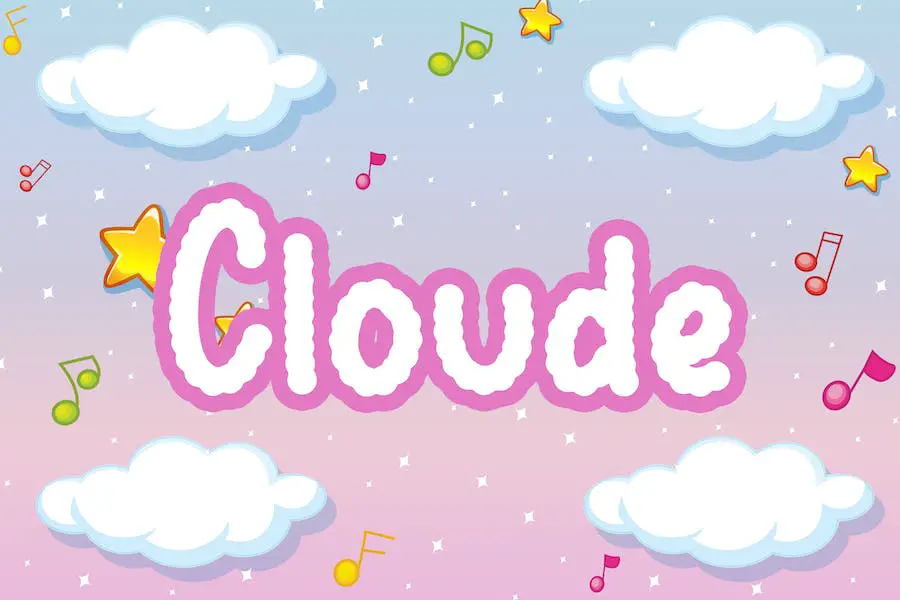
Cloude – 一种非凡的显示字体,为儿童主题设计增添兴奋感! 它非常适合品牌推广、徽标设计、T 恤、书籍封面、社交媒体帖子、广告、产品包装、标签、邀请函等。 Cloude 为任何项目带来独特的风格。
软云
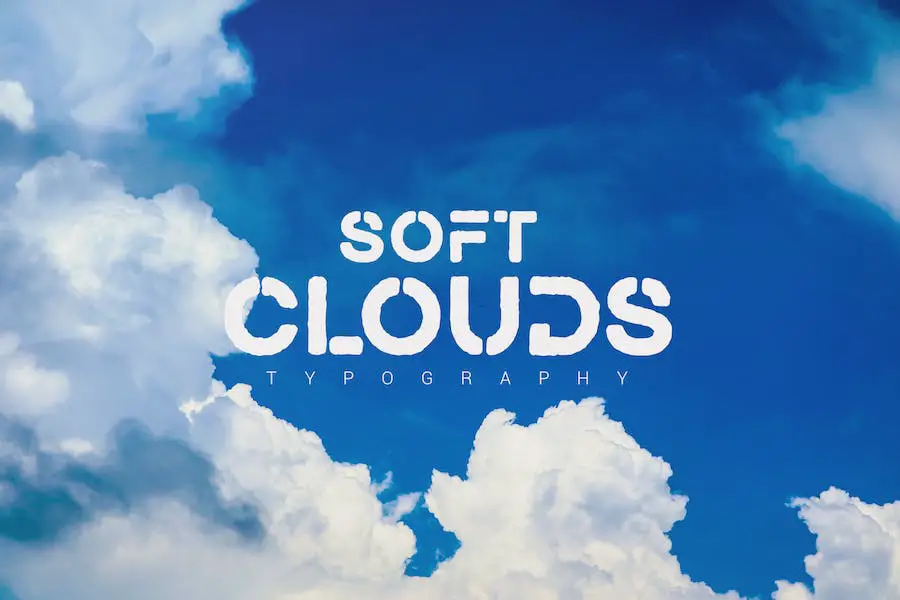
Soft Clouds 是一款出色的字体,提供三种匹配样式,为您的设计项目提供广泛的可能性。 这种字体具有易于阅读的字母,非常适合数字和印刷应用。
无论您是为网站、广告甚至纹身沙龙创建图形,Soft Clouds 都一定能为您的作品增添一丝优雅和独特。
泡沫或云
Foam 或 Clouds 是一种独特的字体,可为 SVG 字体提供逼真的笔刷效果。 它有两种样式:浅色背景上的深色字体,具有多层效果,以及深色背景上的浅色字体,具有屏幕图层效果。
云
The Clouds 是一款出色的字体包,提供 5 种匹配字体,为您的设计项目提供无尽的多功能性。 这些字体无缝地协同工作,让您可以在设计中创造出令人惊叹的变化。 无论您从事数字项目还是印刷项目,这种字体都非常易于阅读。
当谈到图形设计时,找到完美的字体可以让一切变得不同。 有了 The Clouds,您将拥有一系列字体,这些字体不仅相互补充,而且还提供广泛的创意可能性。
每种字体都有自己独特的风格,让您可以尝试并找到最适合您的项目的字体。
榛云
Hazel Clouds 是一款令人惊叹的脚本字体,提供清新和现代的外观。 无论您是从事品牌项目、创建迷人的标题、设计服装还是设计包装,这种字体都是完美的选择。
模仿小丑
Mockey Clown 是一种字体样式,可为您的设计增添动感和奇思妙想。 这种字体具有圆润的边缘、流畅的线条和稍微大胆的外观,非常适合创造时尚和现代的外观。
它提供三种不同的风格,可以混合搭配,让您的设计实现定制化和多功能性。
无论您是在从事面向青年的项目、杂志布局、海报、时尚品牌,还是只是需要为背景图像添加时尚的文字叠加层,这种字体都是时尚且可定制的选择。
扭云
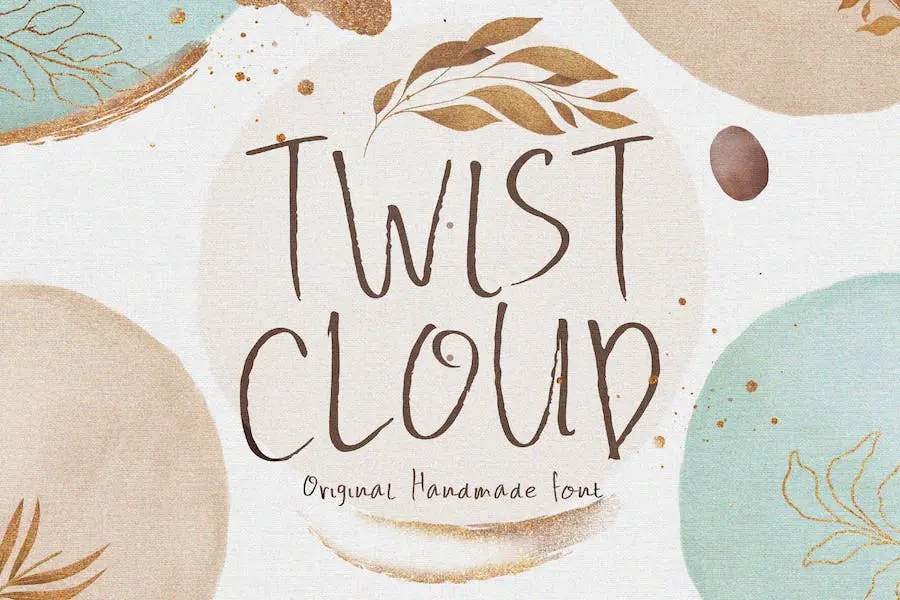
Twist Cloud 是一款将为您的企业带来独一无二的外观的字体。 凭借其独特的手写风格,这种字体可以让您以脱颖而出的方式表达您的品牌个性。
手写完全取决于个性,而这正是您通过 Twist Cloud 所获得的。 每个字母都有其独特的个性,为您的品牌增添个人风格。
无论您是要创建海报、信件、标题、网络博客、社交媒体帖子、故事、横幅、包装、T 恤设计、婚礼请柬还是徽标,这种字体的用途广泛,足以适合任何项目。
云雾缭绕
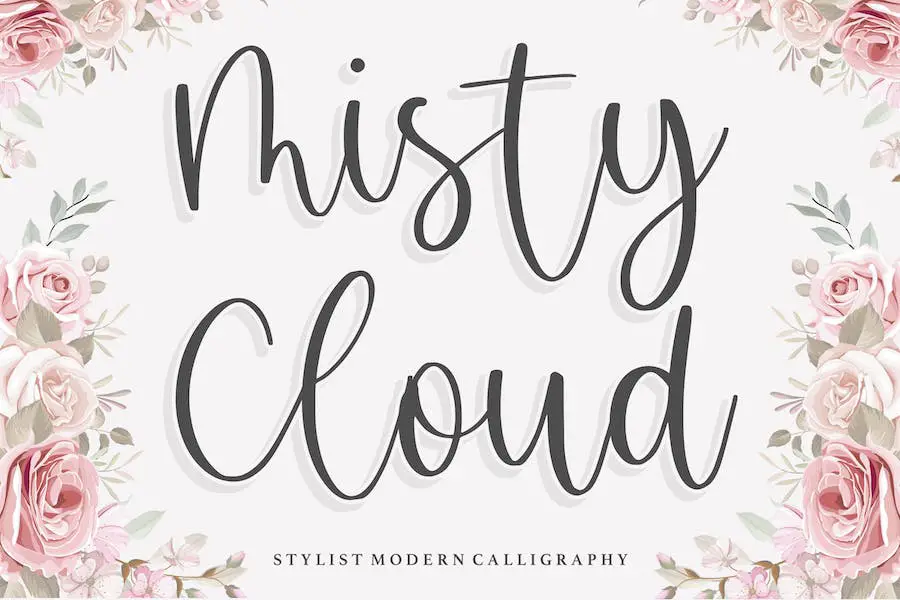
Misty Cloud 是一种时尚的现代书法字体,是任何图形设计师工具包的完美补充。
无论您是在设计产品包装、品牌项目、杂志布局、社交媒体内容、婚礼请柬,还是只是想为您的设计添加富有表现力的触感,Misty Cloud 都能满足您的需求。
蓬松的
Fluffy 是一种令人愉悦的字体,可为任何设计项目带来可爱和异想天开的感觉。 这种字体以其柔软和棉质的外观,捕捉到了空气的轻盈和手写字母的魅力。
Fluffy 的灵感源自云朵和豆子的形状,非常适合在儿童读物、卡通、动画等中营造俏皮而温柔的氛围。
这种字体的蓬松特征使其真正独一无二。 其柔和的曲线给人一种舒适和温馨的感觉,而手写字母般的形式增添了一丝真实感。
棉花云
Cotton Cloud 是一种让人联想到在天空中柔软蓬松的云中飞翔的感觉的字体。 它非常适合增强冒险在线游戏、海报、电影标题、杂志、YouTube 封面、缩略图和社交媒体页面封面的设计。
凭借其轻盈梦幻的外观,棉花云为任何项目增添了一抹奇思妙想。 该字体用途广泛,可在各种环境中使用,使其成为寻求提升设计的图形设计师的绝佳选择。
吉特哈
Jitqha 是一种可爱又有趣的字体,非常适合各种设计项目,尤其是针对儿童的设计项目。
它采用大写字母,为生日邀请函、文具、T 恤设计、标签、徽标、品牌、包装甚至日历增添了有趣和异想天开的感觉。
无论您是在从事儿童活动项目,还是只是想为您的设计带来有趣的元素,Jitqha 都是一个不错的字体选择。
最佳免费云字体
为希望增强项目设计的图形设计师推出一系列最佳免费云字体。 花点时间浏览这篇文章,找到可以提升您的创意作品并使其真正脱颖而出的完美字体。
云
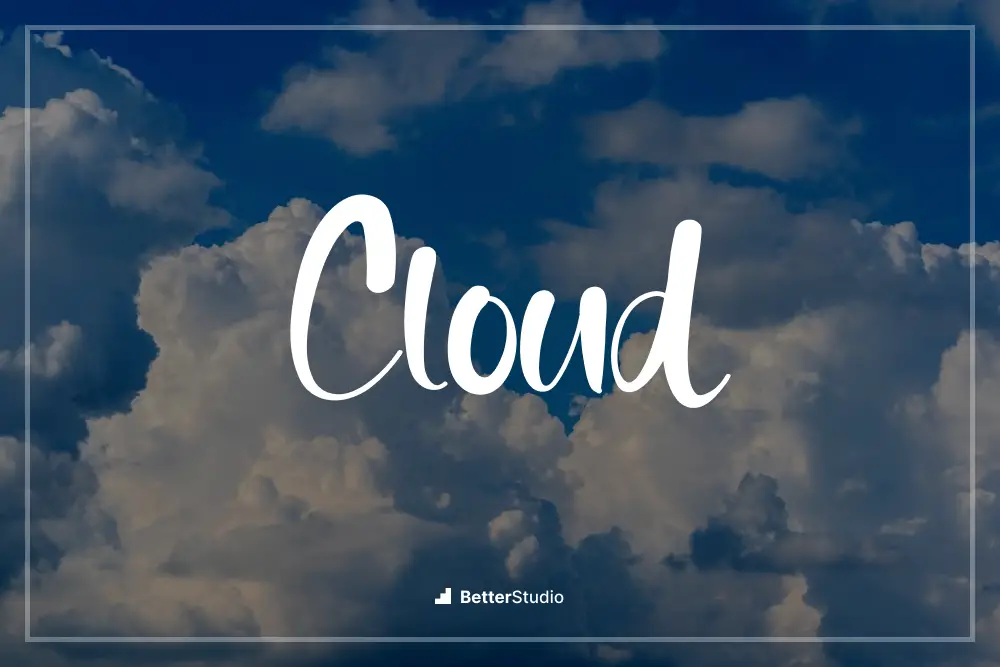
Cloud by Metal Studio 是一款非常适合希望增强项目设计的图形设计师的字体。 凭借其独特的属性和时尚的风格,Cloud 将您的设计提升到新的高度。
Cloud 是一种多功能字体,可为任何项目增添一丝优雅和精致。 其简洁的线条和现代审美使其成为设计师的热门选择。
无论您是在设计徽标、网站还是品牌材料,Cloud 都将使您的设计脱颖而出。
多云的
Cloudy 是一种时尚且多功能的字体,可以增强任何项目的设计。 其时尚而现代的美学使其成为寻求提升工作水平的平面设计师的完美选择。
这种字体给任何设计带来独特和清爽的感觉,增添一丝精致和专业精神。 无论您是在制作徽标、网站还是任何其他创意项目,Cloudy 都一定会做出声明。
其简洁的线条和优雅的曲线营造出引人注目的视觉冲击力,让您的设计脱颖而出。 有了 Cloudy,您的项目将拥有现代而精致的外观,吸引您的观众。
云天
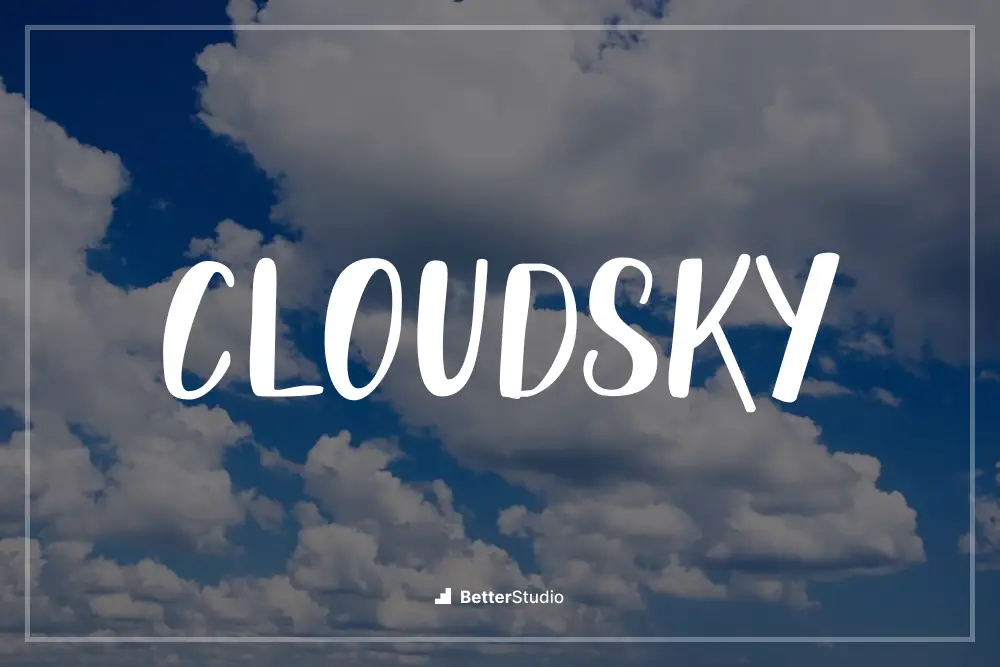
Billy Argel Fonts 的 Cloudsky 是一种斜体字体,非常适合希望增强项目设计的图形设计师。 Cloudsky 凭借其时尚现代的风格,为任何设计增添了一抹精致。
该字体易于阅读且用途广泛,适用于各种项目。 其独特的斜体设计赋予其优雅和创意感。 对于任何希望将自己的工作提升到新水平的设计师来说,Cloudsky 是一款必备字体。
蓝天
Blue Sky 是由 Senekaligrafika 创建的一种字体,称为“It Font”。 它为图形设计师提供了风格和多功能性的独特组合。 Blue Sky 以其现代时尚的设计脱颖而出,非常适合为任何项目增添一丝优雅。
凭借其简洁的线条和平滑的曲线,这种字体一定会吸引眼球并增强整体设计。 无论您是在制作徽标、网站还是任何其他设计项目,Blue Sky 都是一种可以将您的工作提升到新水平的字体。
Blue Sky 的突出特点之一是它的可读性。 字体的清晰度确保您的信息易于被观众理解,从而使您能够有效地传达您的想法。
下云
Down Cloud 是一款专为希望增强其项目的图形设计师而设计的字体。 它提供了一系列可以提升设计的属性,从独特的风格到多功能性和易用性。
该字体以其现代时尚的外观脱颖而出,非常适合当代设计。 简洁的线条和锐利的边缘为您的项目带来专业和精致的感觉。
Down Cloud 具有多种重量和款式,让您可以尝试并找到完美的设计。 其可读性可确保您的信息清晰传达,而其时尚的设计则增添了一丝创造力。
经常问的问题
云字体,也称为网络字体,是存储在服务器上并通过云传送到您的网站或应用程序的字体。 通过使用云字体,您可以确保网站的排版在不同的浏览器和设备上看起来一致。
使用云字体有几个优点。 首先,与标准网络安全字体相比,它们提供了更广泛的字体选项。 这使您可以从庞大的字体库中进行选择,确保您的网站以独特且有吸引力的排版脱颖而出。
此外,云字体针对网络使用进行了优化,确保更快的加载时间和更好的性能。 最后,云字体易于扩展,这意味着它们可以调整为不同的大小而不会失去清晰度,使您的网站更易于访问和用户友好。
结论
总之,我们探索了 2023 年 17 种最佳云字体,包括免费和高级选项。 我们已经讨论了选择正确字体来增强图形设计项目的重要性。
无论您想要增添一丝优雅还是现代气息,这些云字体都能满足您的需求。